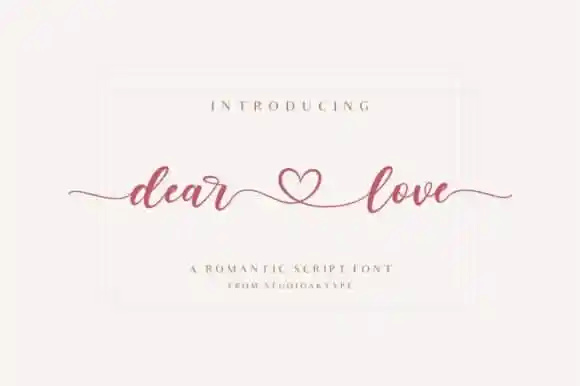
Dear Love Calligraphy Font – Fonte Grátis
Dear Love Calligraphy Font
Descubra a encantadora Dear Love Calligraphy Font no seu projeto atual. Esta elegante fonte script, criada pelo site de design 99designs, traz uma paleta de letras tanto maiúsculas quanto minúsculas, alternativas de desenho suave, ligaturas e símbolos multilíngues. O PUA encoding permite a você acessar facilmente todos os traços e alternativas com um clique. Seu destaque são as linhas lisas e graciosas, combinadas com alternativas lindas, mantendo sempre sua essência clássica da tipografia enquanto também tem o toque contemporâneo que você precisa. O Dear Love Calligraphy Font é perfeito para projetos de amorosos cartões, adesivos ou selos. Suavizar palavras e frases com essa fonte, sem dúvida, fará seu design brilhar mais ainda. O ideal para aqueles que desejam dar um toque especial a suas criações digitais. Experimente agora e veja como sua arte ganha um novo encanto!